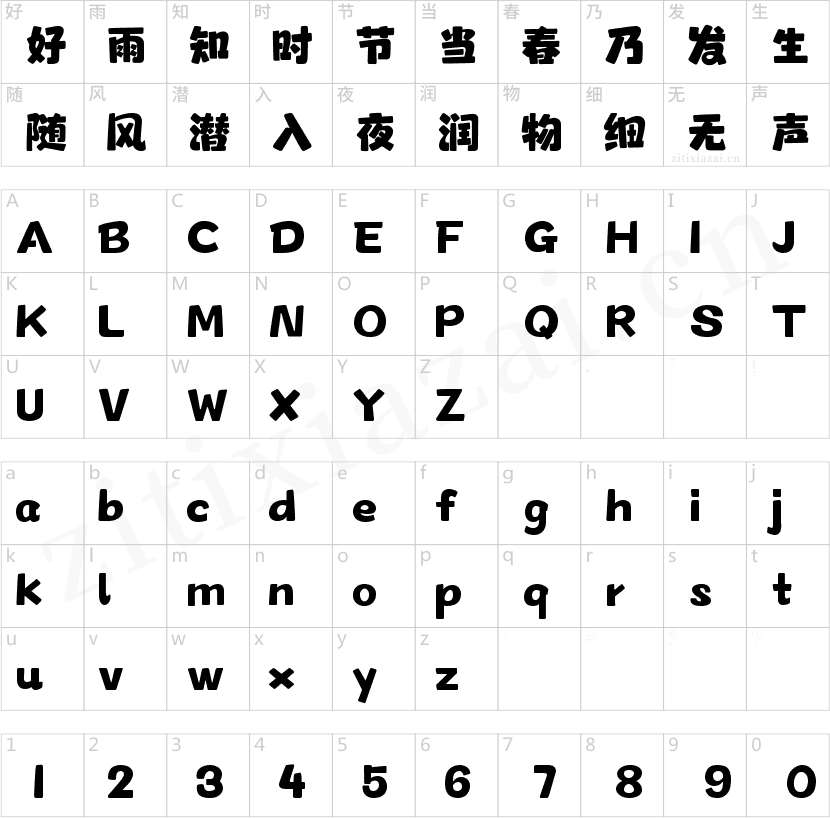
字魂幸福兔崽体
字魂幸福兔崽体,这款字体结构工整、笔画清晰,兼顾美观与易读性,适用于标题、正文、海报、包装、LOGO 等多种场景。字形优雅稳定,风格百搭耐看,适配日常排版与创意设计,让文字呈现更舒适、更具质感。字魂幸福兔崽体一笔一画,皆是细节,以均衡的比例、流畅的线条打造舒适视觉体验,字形端正大气,风格简约现代。无论是商业设计、品牌宣传还是日常排版,都能轻松驾驭,让文字更有格调与力量。字魂幸福兔崽体字体下载。